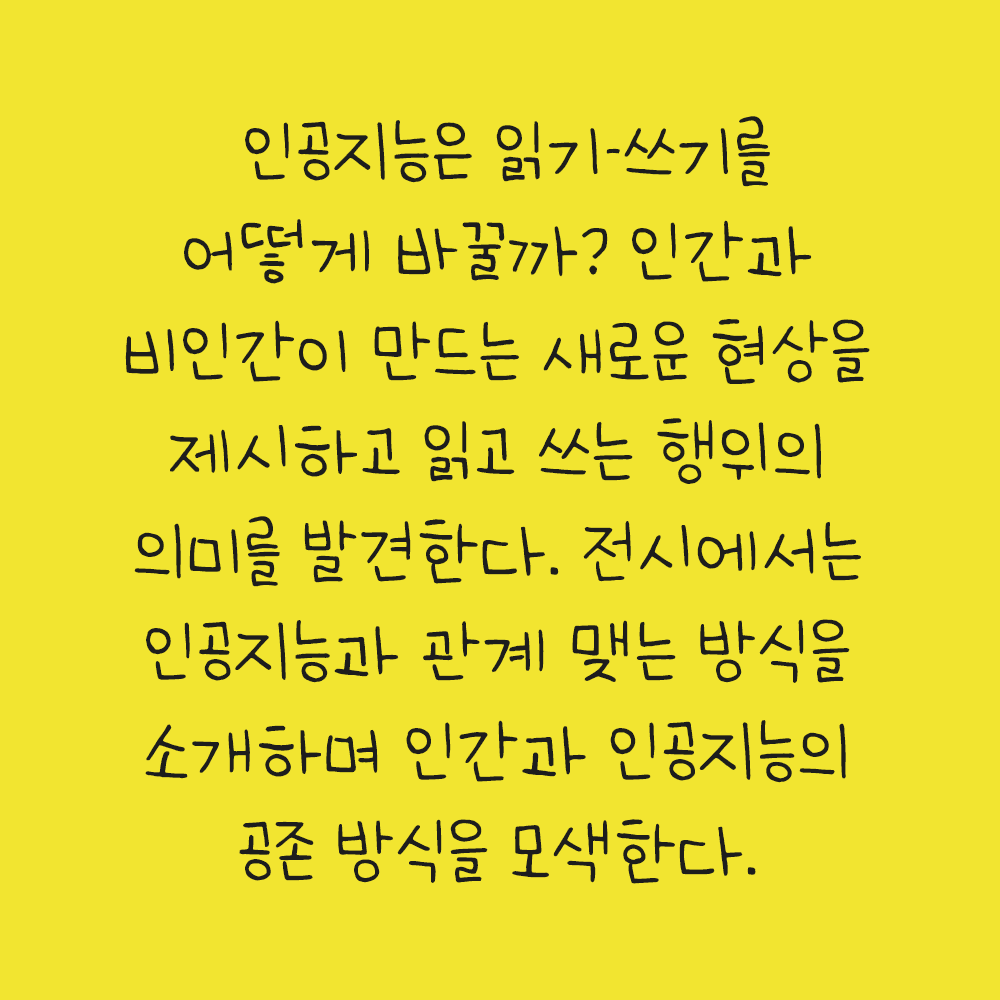
그리운X국한박 사랑스러운
GriunXHangeul Sarang seu reo un
그리운X국한박 사랑스러운 소개
제5회 한글실험프로젝트 《글(자)감(각): 쓰기와 도구》 The 5th Hangeul Design Project 《Senses of Writing: Tools & Perception》 전시기간: 2025.11.19.~2026.3.22. 전시장소: 문화역서울284 RTO 주최·주관: 국립한글박물관 이 손글씨 폰트는 국립한글박물관 제5회 한글실험프로젝트 《글(자)감(각): 쓰기와 도구》 전시 연계 이벤트를 통해 제작되었습니다. 손의 움직임과 쓰는 감각을 그대로 담아, 쓰기의 경험을 폰트로 확장합니다.